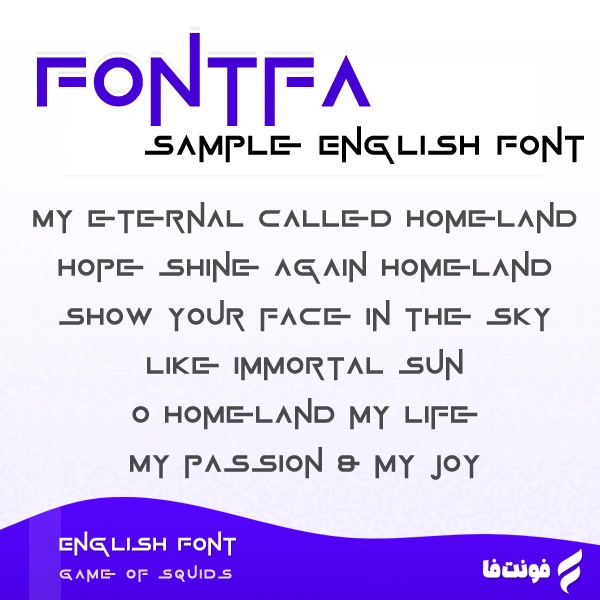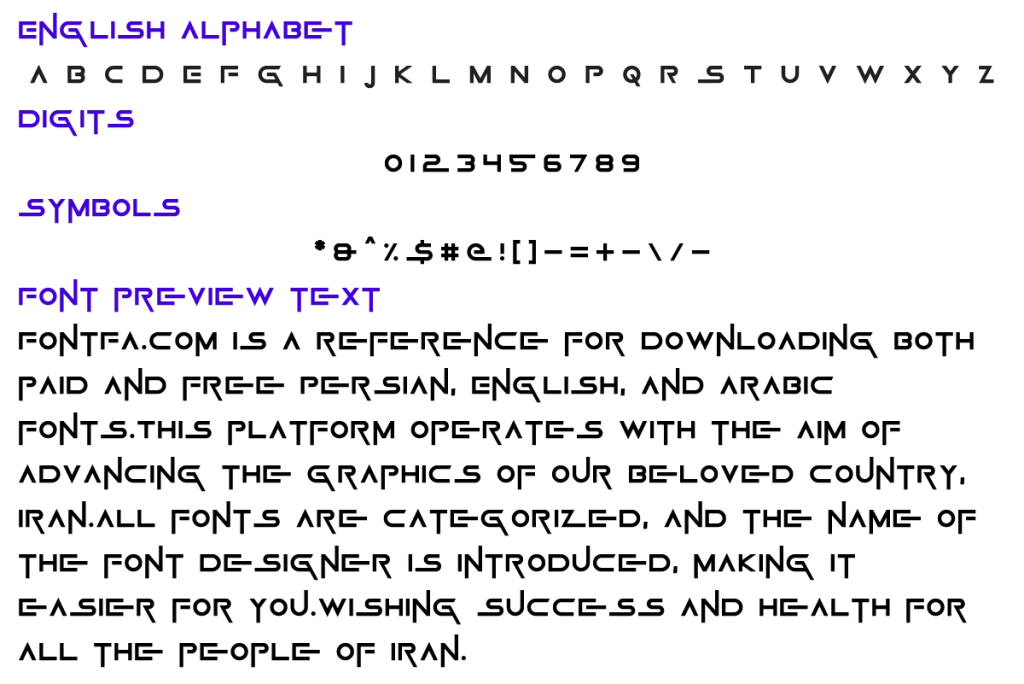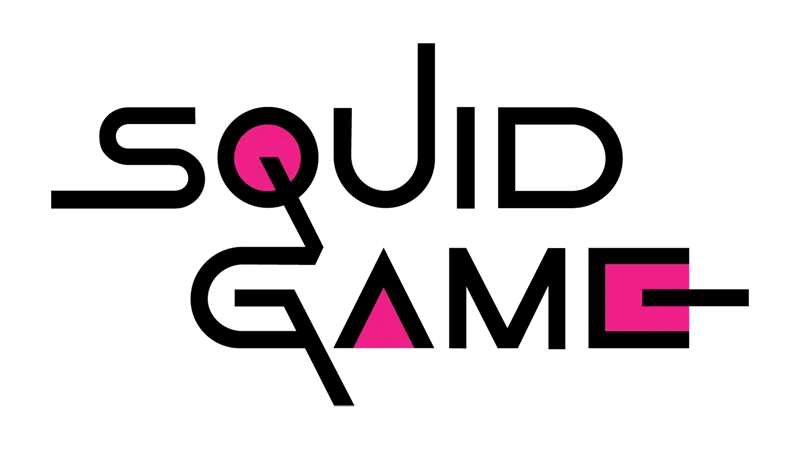
پیشنمایش فونت اسکویید گیم
فونت انگلیسی اسکویید گیم - Game Of Squids
توضیحات و معرفی فونت اسکویید گیم
فونت انگلیسی اسکویید گیم ( Game Of Squids ) از مجموعه فونت های آزاد می باشد، همچنین نوع فونت تایپوگرافی و هندسی می باشد.
فونت فوق العاده زیبای معرفی شده در سال 2021 توسط Darrell Flood برای سریال بازی مرکب Squid Game طراحی و ساخته شده است.
قلم طراحی شده برای بازآفرینی حس و حال علمی/تخیلی کلاسیک، به قدری نوستالژیک و جذاب است که حتی هریسون فورد را هم خوشحال می‌کند.
فونت اسکویید گیم امروزه بیش از پیش در صنایع مختلف به کار گرفته می شود تا برندها ظاهری خلاقانه تر و تاثیرگذارتر داشته باشند.
همچنین فونت Game Of Squids در یک وزن معمولی است.
نگاهی بیندازید به تصویر زیر که نمونه‌ای از این تایپ فیس را در شعر «وطن» نمایش می دهد.
دموی فونت Game Of Squids
لوگو جذاب و فوق العاده زیبای سریال اسکوید گیم نوشته شده با همین تایپ فیس
لوگو اسکویید گیم